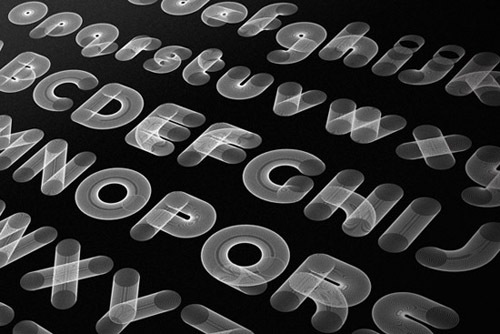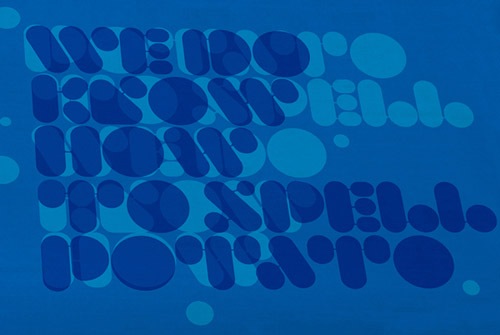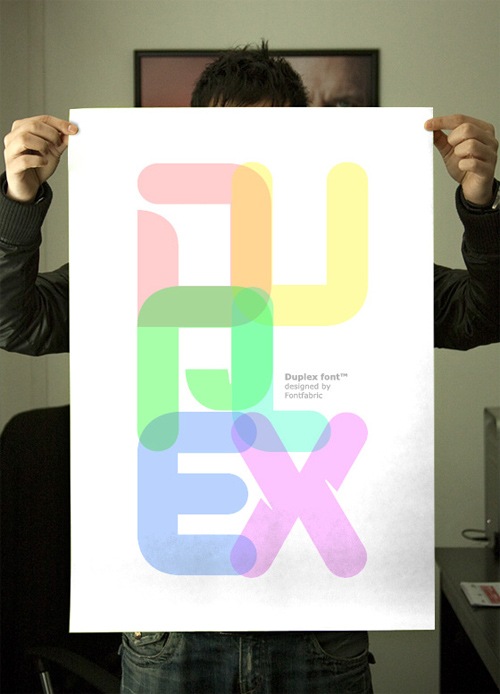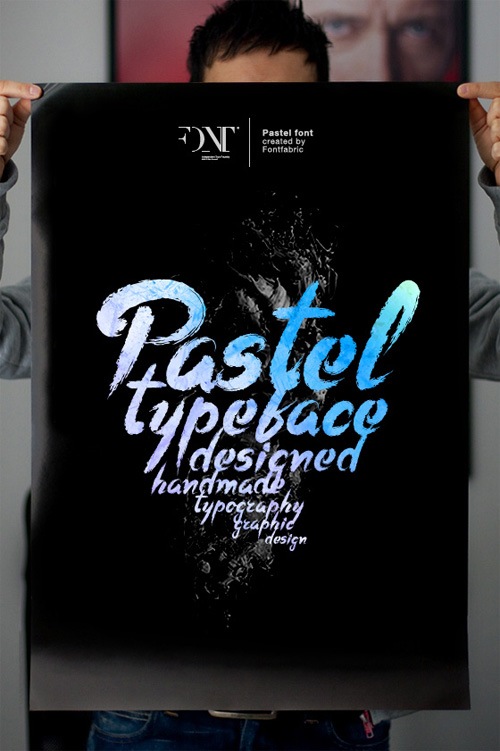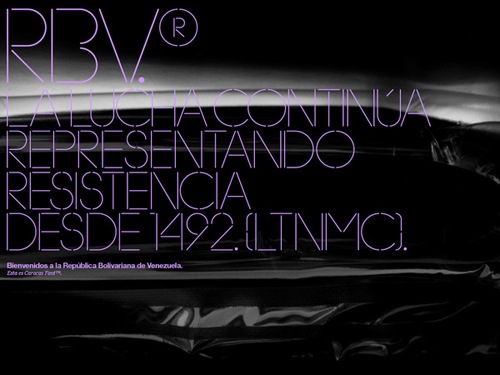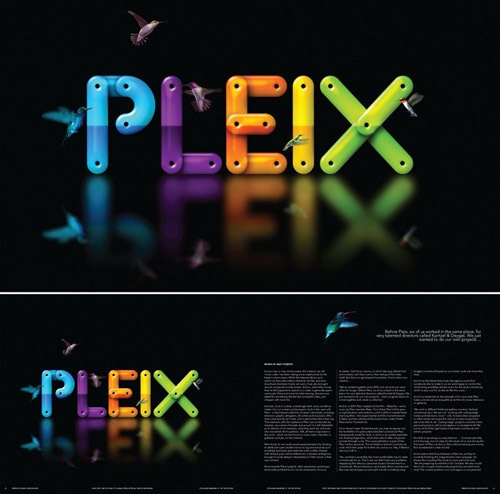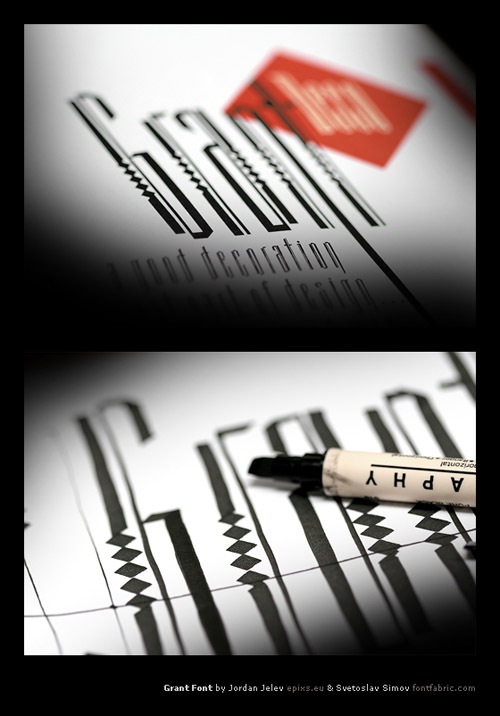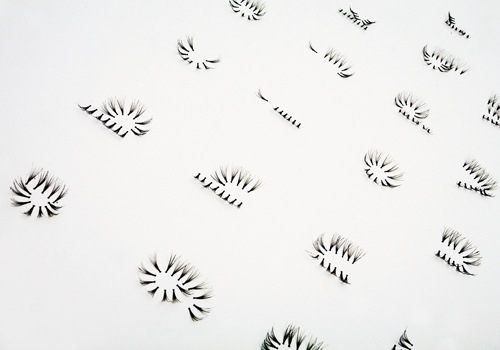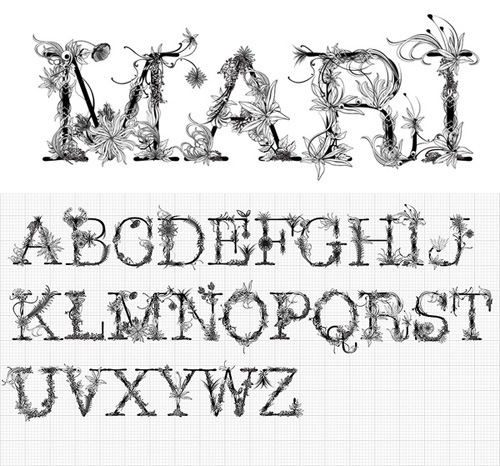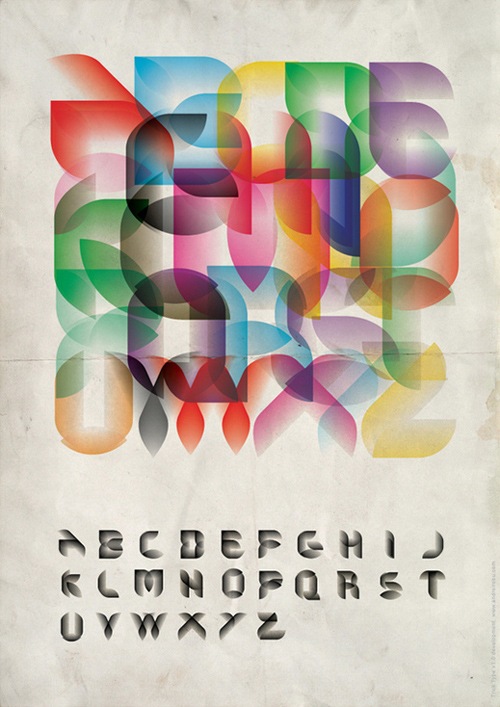
18 типографических дизайнов
18-типографических-дизайновВ наши дни множество дизайнеров уделяют огромное внимание шрифтам. Поэтому, в этой подборке вы увидите 18 примеров типографического дизайна, собранных для вашего вдохновения. Это одни из самых креативных типографических примеров, созданных талантливыми дизайнерами.
креативный шрифт в виде пружин
шрифт из ресниц
шрифт в цветах
креативный красочный шрифт
угловатый шрифт
узоры в типографике
примеры креативной типографики
стильная полупрозрачная типографическая надпись
объемный типографический шрифт
типографический шрифт из треугольников
полосатая типографика
округлый типографический шрифт
креативный трафаретный шрифт
типографический постер
постер с типографическим шрифтом
стильная типографика
яркая типографика
узорчатый типографический шрифт